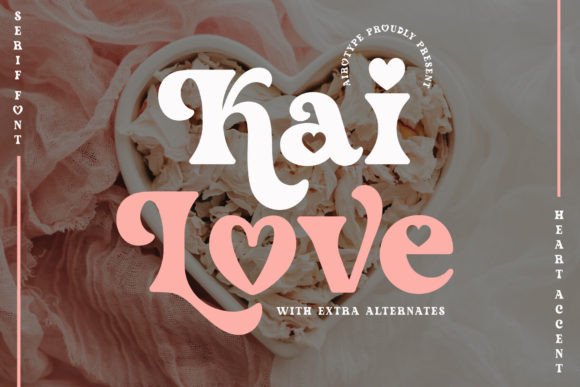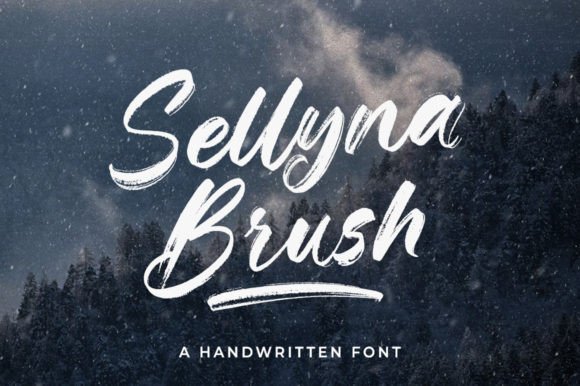
Beautiful Fonts
Jika Anda mencari aset berkualitas tinggi seperti Beautiful Fonts, paket premium ini adalah pilihan fantastis untuk proyek kreatif Anda.
Dibuat dengan presisi, Beautiful Fonts menyediakan vektor yang bersih, tipografi yang halus, serta lisensi komersial untuk ketenangan pikiran Anda.
Baik Anda membuat produk POD (Print on Demand), undangan pernikahan, atau grafis media sosial, Beautiful Fonts adalah pilihan yang sangat ideal.